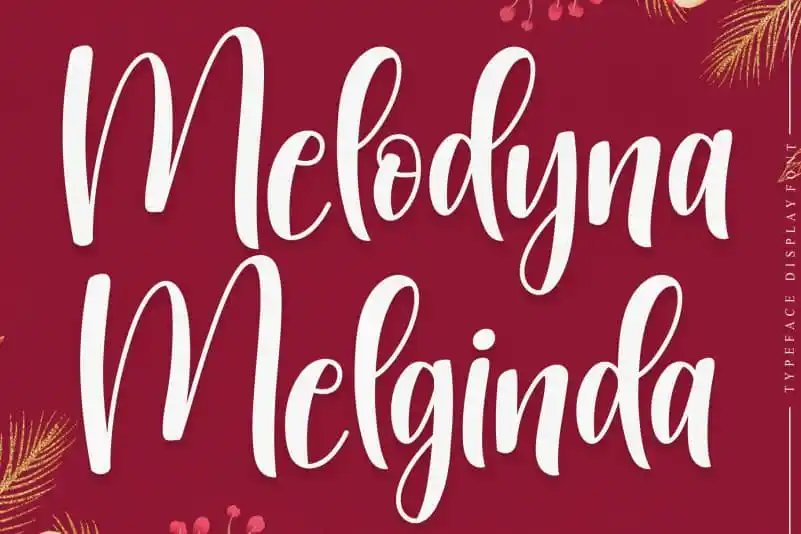
Melodyna Melginda Script Font – Fonte Grátis
Melodyna Melginda Script Font
Aqui está uma breve descrição natural e envolvente para a página de download da fonte “Melodyna Melginda Script Font”, adaptada ao tom pedagógico do blog de recursos gráficos: Embrenhados no mundo das fontes, temos o privilégio de apresentar uma nova adição à nossa coleção: “Melodyna Melginda Script Font”. Esta fonte é um produto especial e criativo projetado para fornecer experiências únicas aos nossos clientes. Com seu estilo elegante e personalizado, essa fonte é perfeita para criar designs que destacam sua identidade visual. O nome “Melodyna Melginda” carrega conotações de delicadeza e beleza, embora seja tecnicamente uma combinação de nomes masculinos. A primeira parte, Melodyna, sugere melodias suaves e acordes perfeitos, enquanto Melginda evoca um sentimento de elegância e arquitetura. Seu design elegante permite que você personalize qualquer projeto com uma pitada de delicadeza e sofisticação. A “Melodyna Melginda Script Font” não é apenas uma ferramenta de escrita, mas também uma arte visual. Ela oferece os recursos essenciais para criar textos belamente formados em diferentes tamanhos e formatos. Este produto está destinado a designers que buscam um toque refinado em seus projetos, seja para o design gráfico impresso ou digital. A “Melodyna Melginda Script Font” é uma fonte de qualidade que reflete os melhores aspectos do trabalho profissional: criatividade, excelência e atenção ao detalhe. Eles podem ser usados individualmente ou combinados com outras fontes para criar um design único. Sem dúvida, a “Melodyna Melginda Script Font” será uma escolha inteligente para qualquer designer que busca uma fonte única para seus projetos. Esta fonte está disponível de forma gratuita e pode ser baixada facilmente em nosso site oficial. Se você está procurando por algo diferente no mercado de fonts, essa fonte é a escolha certa para complementar sua biblioteca de fontes personalizadas.